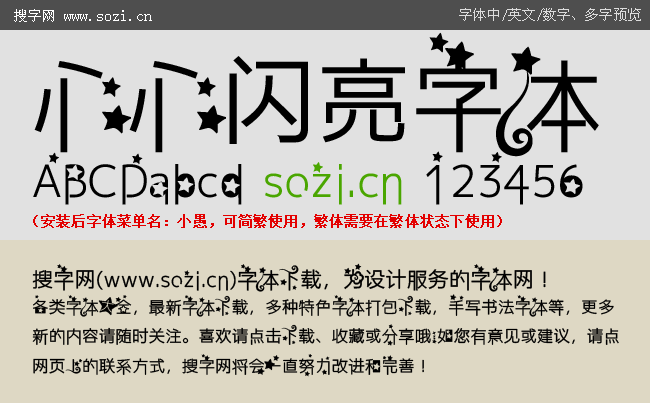
心心閃亮字體
搜字網(wǎng)給大家提供一款心心閃亮字體手機(jī)中文字體下載。這款手機(jī)字體是以黑體字體為原形,一些筆畫(huà)被替換成了卡通花紋與圖案。即有黑體字端正易認(rèn)的特點(diǎn),又帶有一點(diǎn)卡通風(fēng)格,是一款非常可愛(ài)的卡通字體,特別適合喜歡手機(jī)字體個(gè)性一些的朋友在手機(jī)上安裝使用。